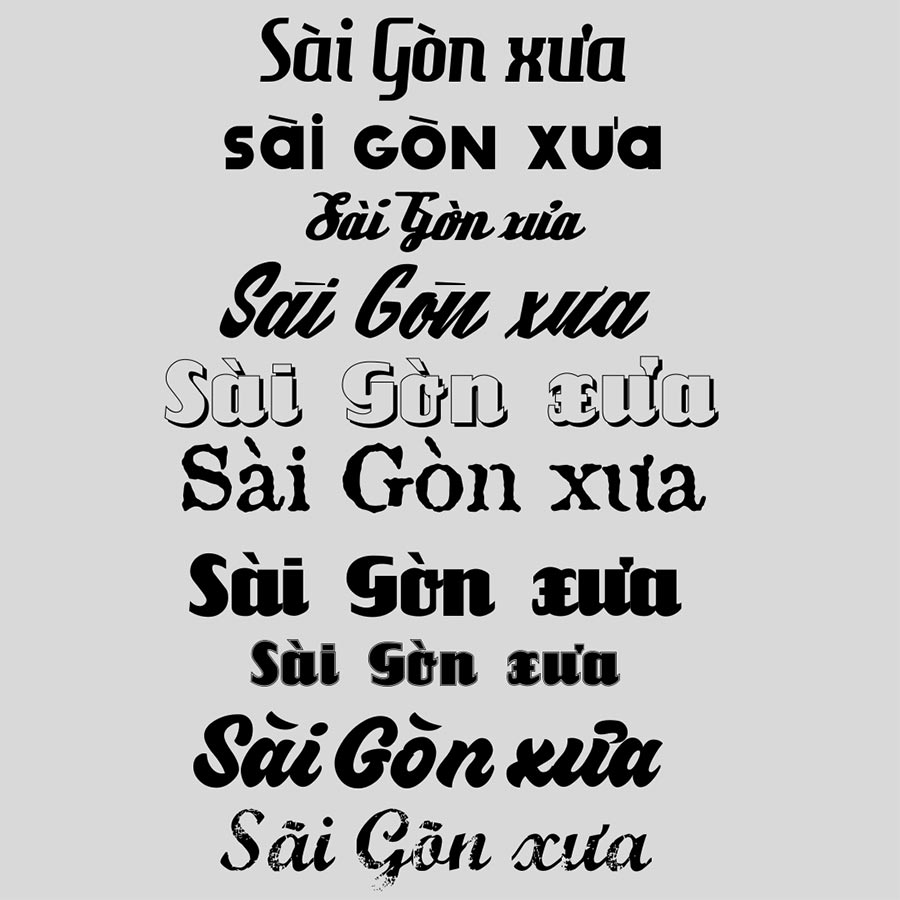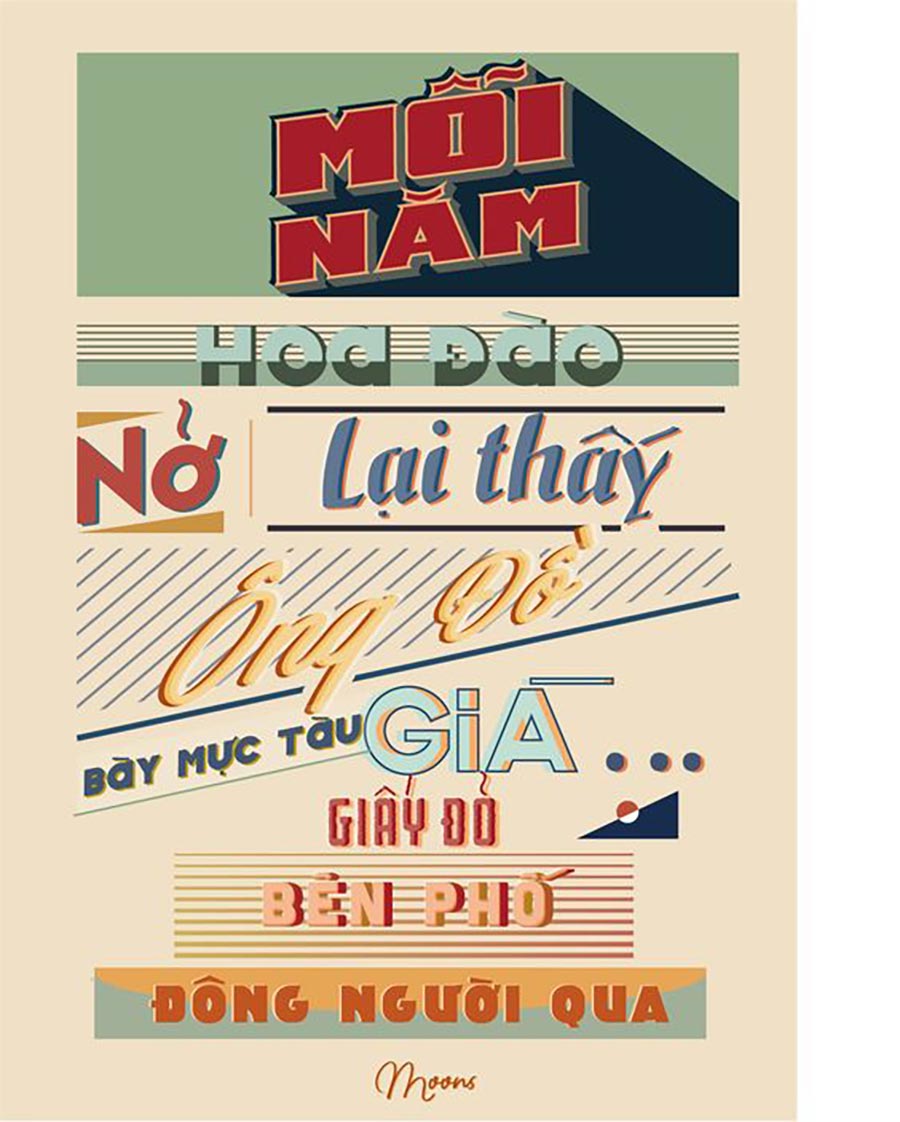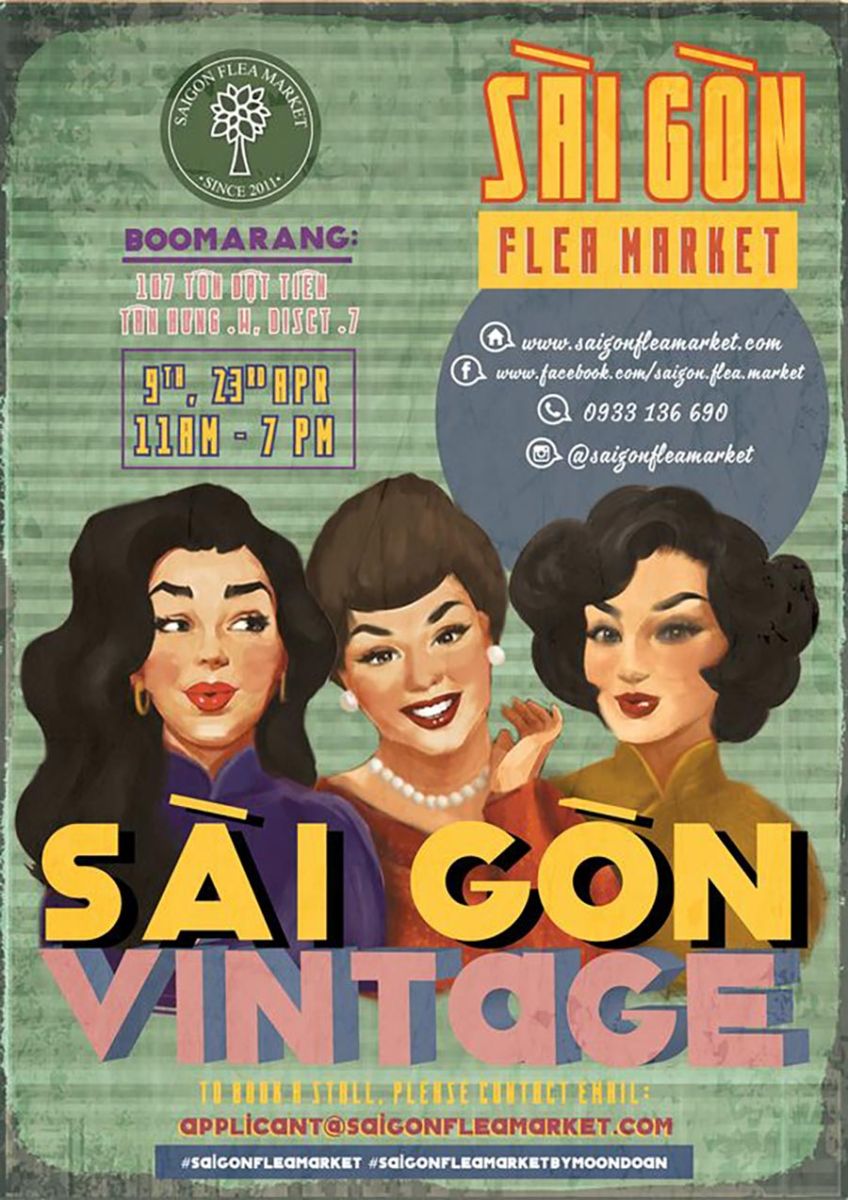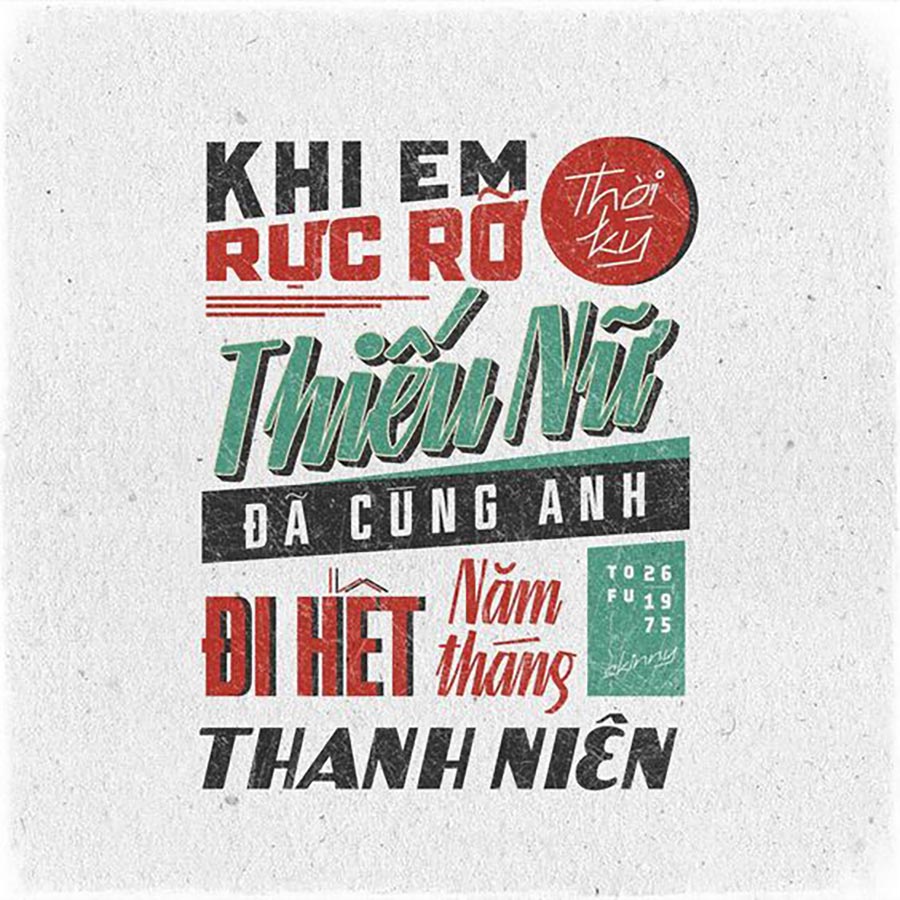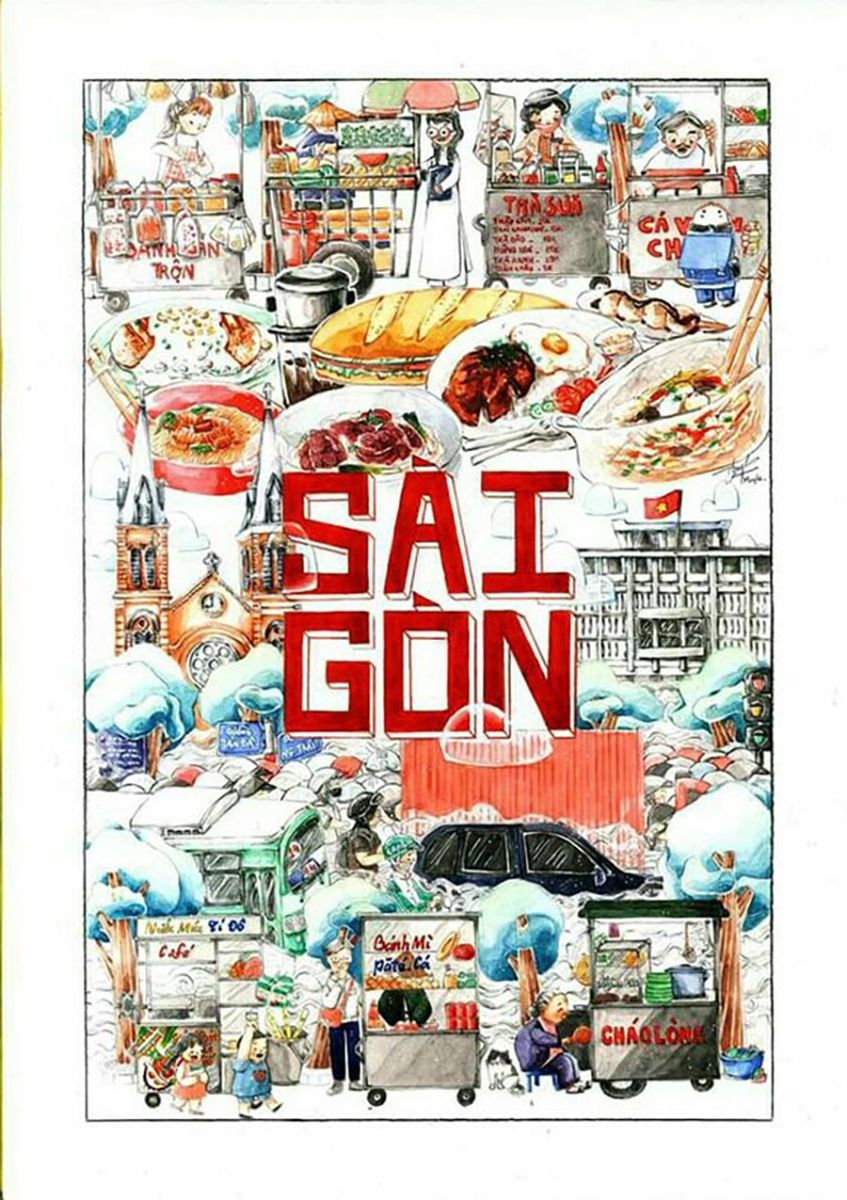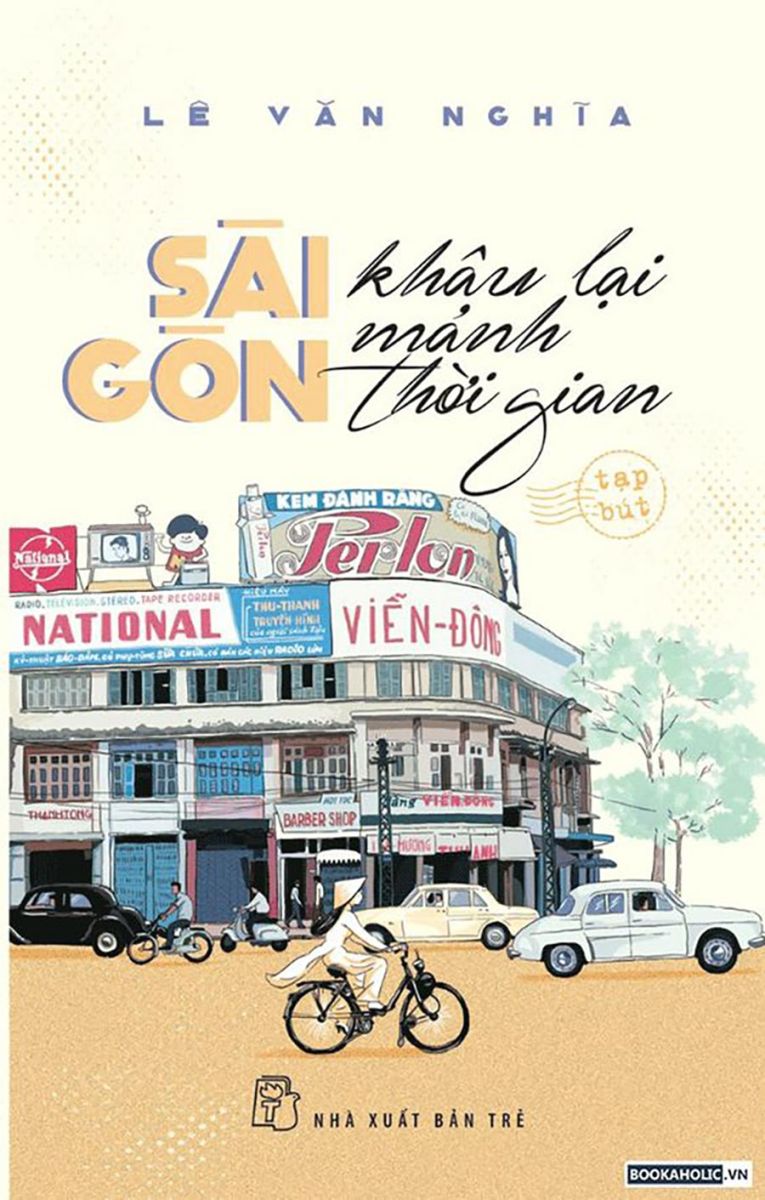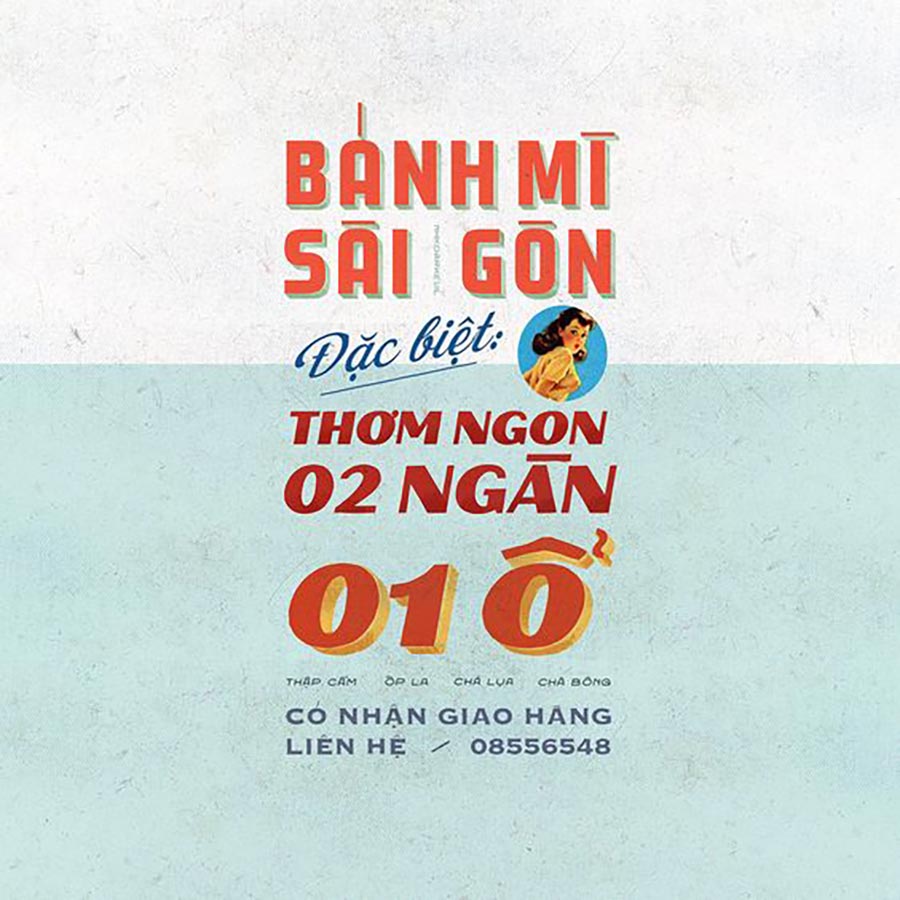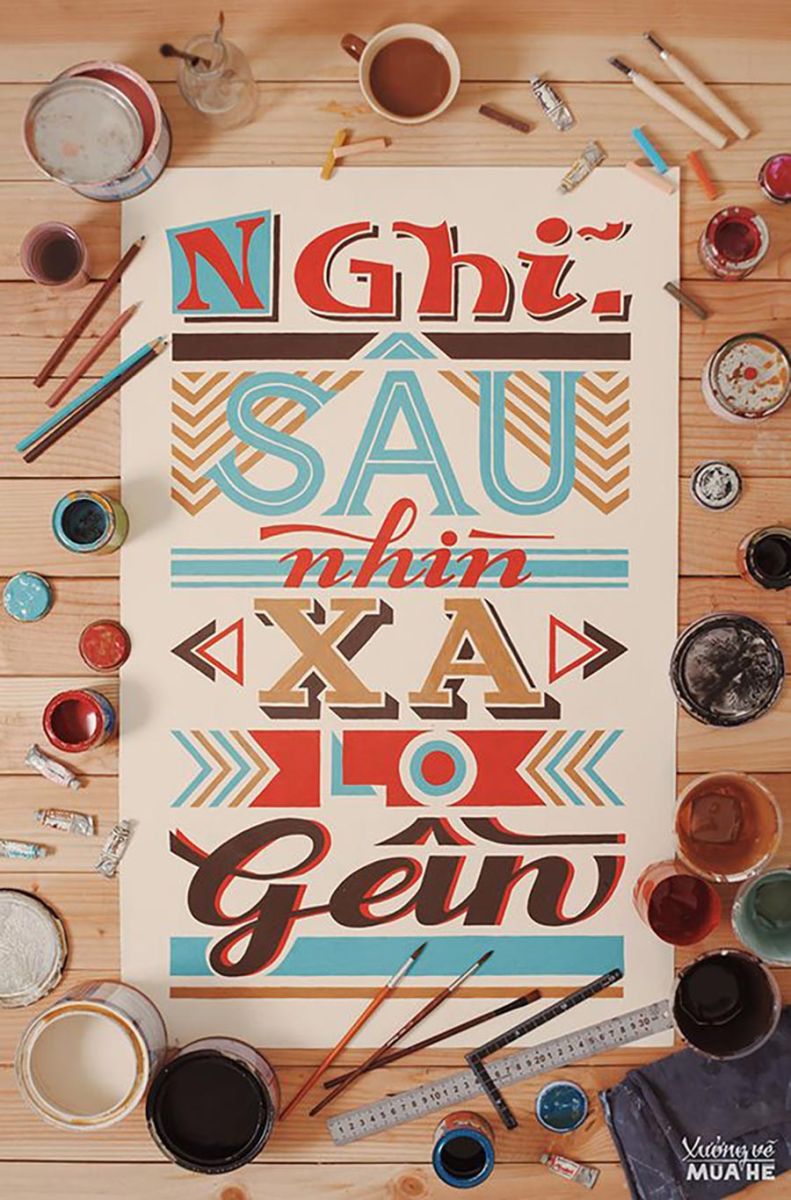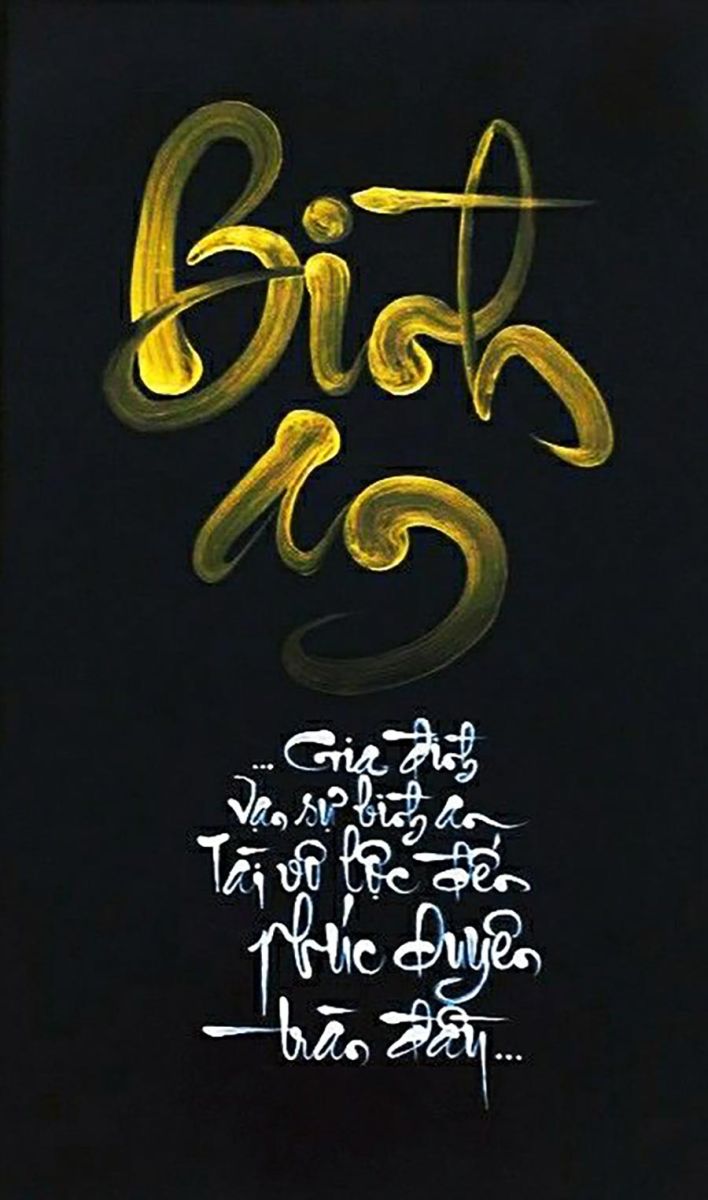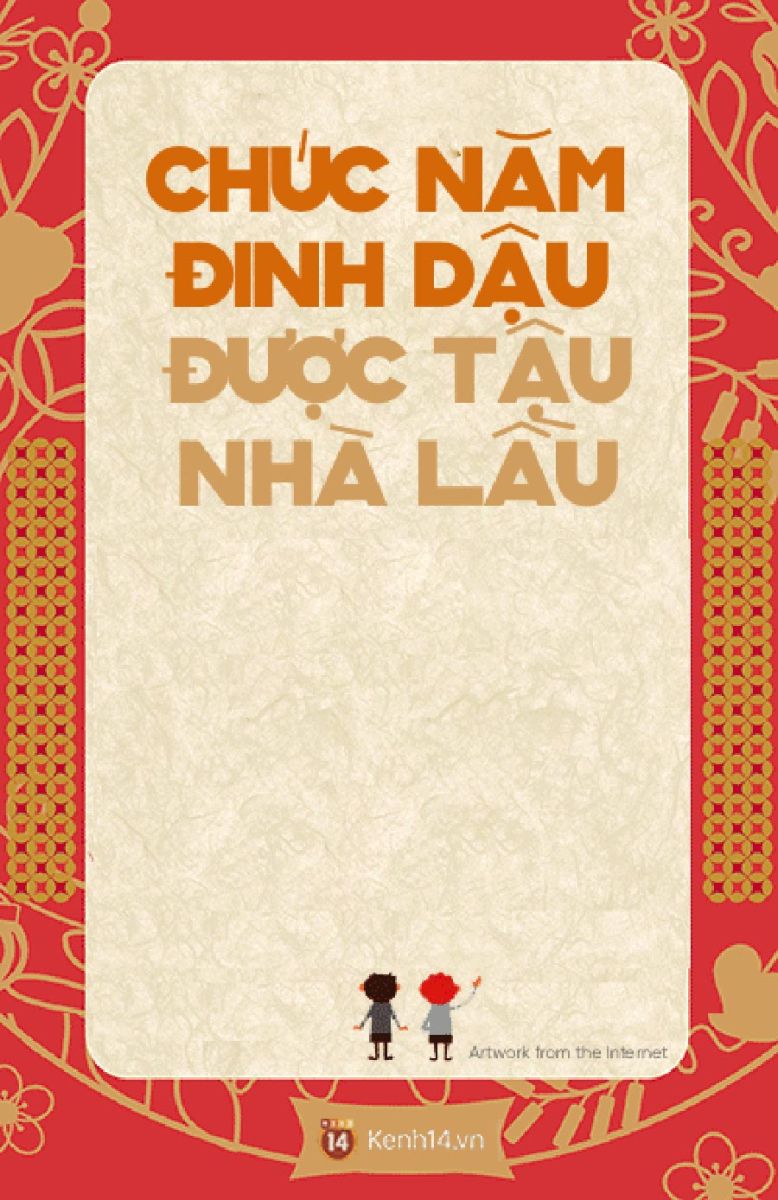
Chia Sẻ Miễn Phí 500 Font Chữ Sài Gòn Xưa Việt Hóa Siêu Đẹp
Trong thời đại phát triển mạnh mẽ của thiết kế đồ họa và sáng tạo nội dung, việc sở hữu những bộ font chữ độc đáo và mang đậm dấu ấn văn hóa luôn là yếu tố quan trọng giúp các nhà thiết kế tạo nên sự khác biệt. Hiểu được nhu cầu này, sadesign.vn đã mang đến một món quà đặc biệt dành cho cộng đồng thiết kế 500 font chữ Sài Gòn xưa Việt hóa siêu đẹp hoàn toàn miễn phí.
Tầm Quan Trọng Của Font Chữ Sài Gòn Xưa
Font chữ không chỉ đơn thuần là công cụ để trình bày nội dung mà còn là một phần quan trọng trong việc truyền tải thông điệp và cảm xúc. Những font chữ mang phong cách Sài Gòn xưa gợi nhớ về một thời kỳ hoài cổ, với nét đẹp truyền thống pha lẫn chút hiện đại của thời kỳ trước. Đây là nguồn cảm hứng tuyệt vời cho các dự án thiết kế mang tính hoài niệm, quảng bá văn hóa hoặc sáng tạo nội dung độc đáo.
Với sự Việt hóa tỉ mỉ, bộ font này không chỉ giữ nguyên được tinh thần của kiểu chữ gốc mà còn đảm bảo tính tương thích cao với tiếng Việt, giúp người dùng dễ dàng áp dụng trong mọi dự án thiết kế.
Điểm Nổi Bật Của Bộ Font Chữ
1. Đa dạng phong cách: Bộ sưu tập bao gồm nhiều kiểu chữ khác nhau, từ thanh lịch, cổ điển đến phá cách, đáp ứng nhu cầu đa dạng của các nhà thiết kế.
2. Chất lượng cao: Các font chữ được tối ưu hóa để sử dụng trên cả nền tảng kỹ thuật số và in ấn, đảm bảo độ sắc nét và tính thẩm mỹ.
3. Việt hóa hoàn chỉnh: Tất cả các font đều được Việt hóa cẩn thận, hỗ trợ đầy đủ các dấu và ký tự tiếng Việt.
Bộ sưu tập 500 font chữ Sài Gòn xưa Việt hóa từ sadesign.vn không chỉ là món quà ý nghĩa dành cho cộng đồng thiết kế mà còn góp phần bảo tồn và lan tỏa những giá trị văn hóa đặc trưng của Việt Nam. Đây là cơ hội tuyệt vời để các nhà thiết kế khai thác nguồn tài nguyên độc đáo này và áp dụng vào các dự án sáng tạo.